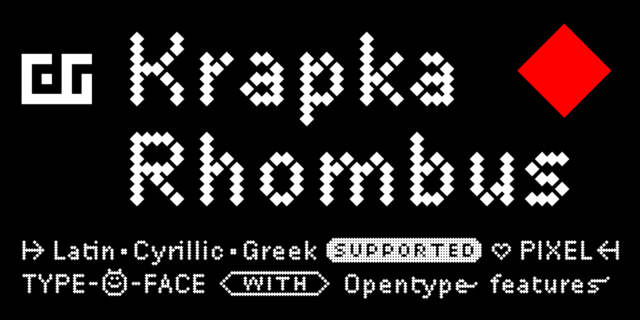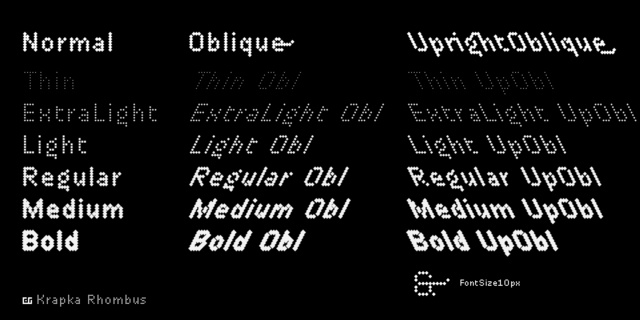
В этом шрифтовом семействе пиксель имеет ромбическую форму. Шрифт поддерживает функции OpenType и содержит капитель, лигатуры, минускульные цифры, дроби и индексы, исторические формы, стилистические наборы и росчерки. Также присутствуют символы, стрелки, и даже эмодзи. Для небольших текстов рекомендуется использовать DR Krapka Rhombus FontSize10px с размером шрифта ровно 10 пикселей. Семейство шрифтов DR Krapka Rhombus поддерживает европейские языки на основе латиницы, кириллицу, в том числе азиатскую, и греческий алфавит. Если вы хотите использовать шрифты с другой формой пикселей, есть и другие семейства DR Krapka: DR Krapka Square (квадраты), DR Krapka Round (круги). Шрифт разработал Дмитрий Растворцев в 2020 году.
Функции семейства DR Krapka RhombusПрименение в макете:
Ассоциации c семейством DR Krapka RhombusКачества и характер: